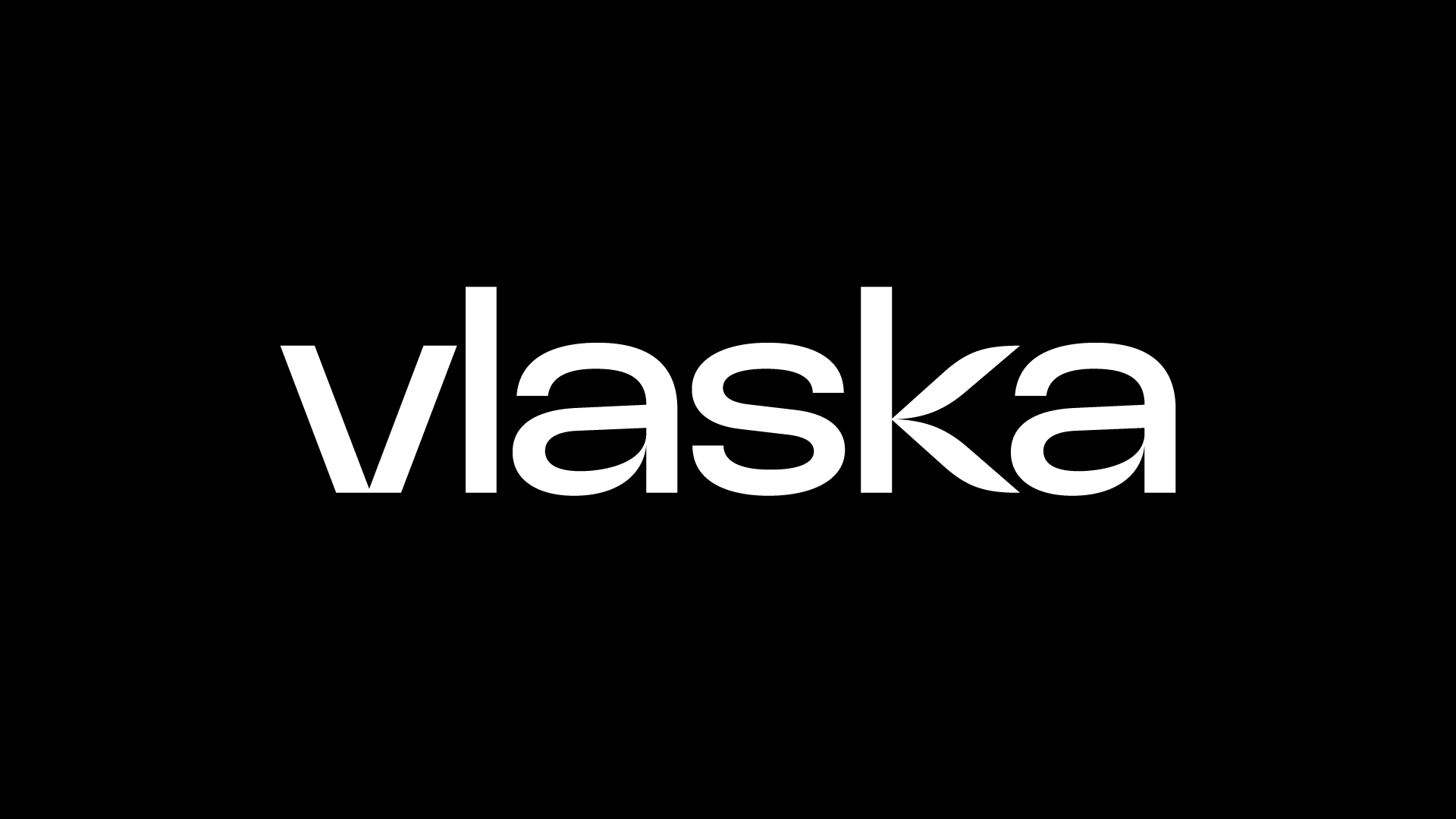
Vlaska
Logo pre kozmetický salón. Sans-serifové logo je postavené na kombinácii ostrých geometrických prvkov a plynúcich ťahov, čo dáva logu moderný a elegantný charakter.